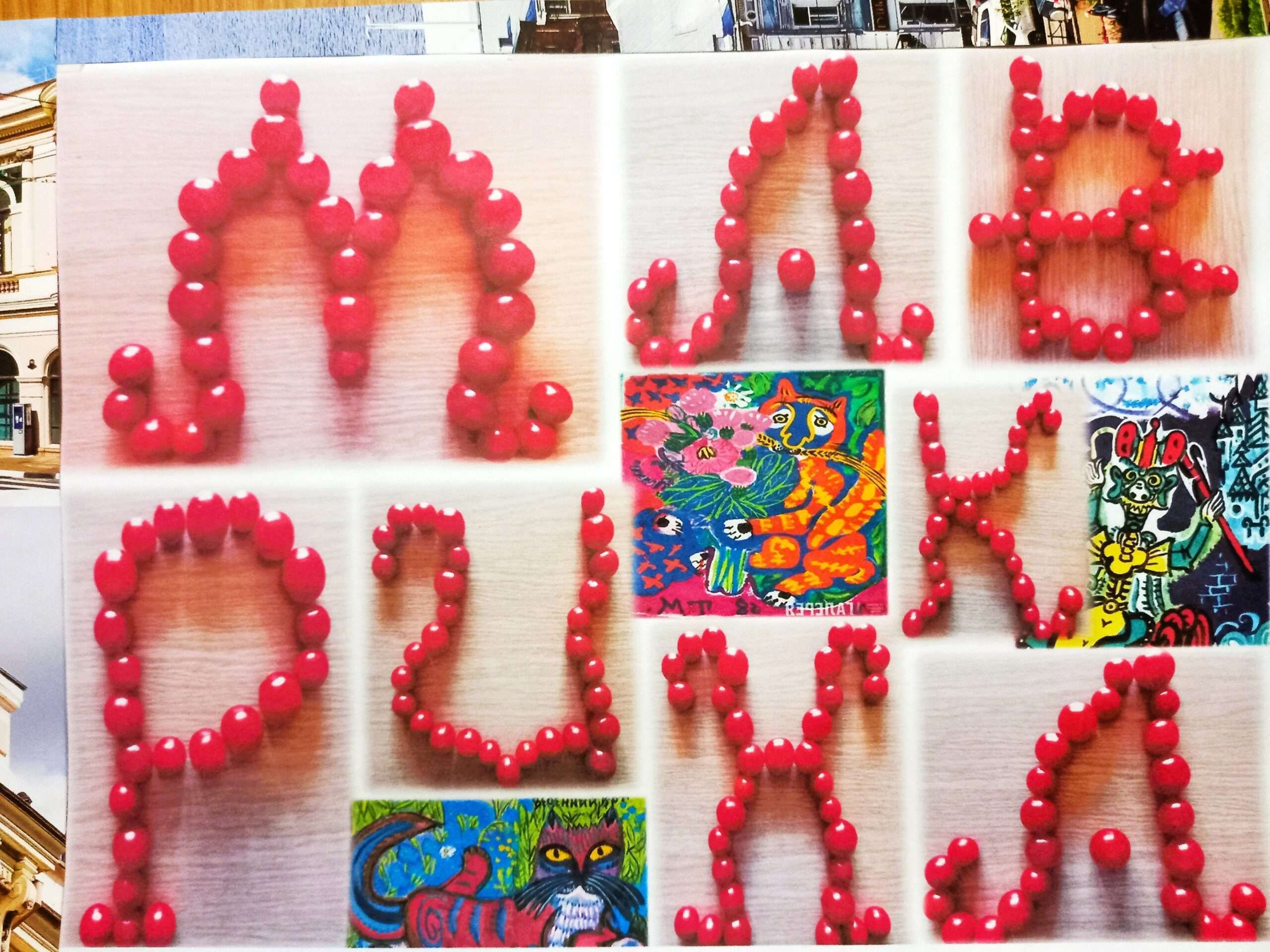
Вкус буквы. Шрифт Помидорка-Мавринка.
Буквы выполнены из маленьких помидоров сорта черри. Это можно сказать слияние фантазии, живой природы и возможности восприятия мира на вкус. В наличии есть весь алфавит и цифры.